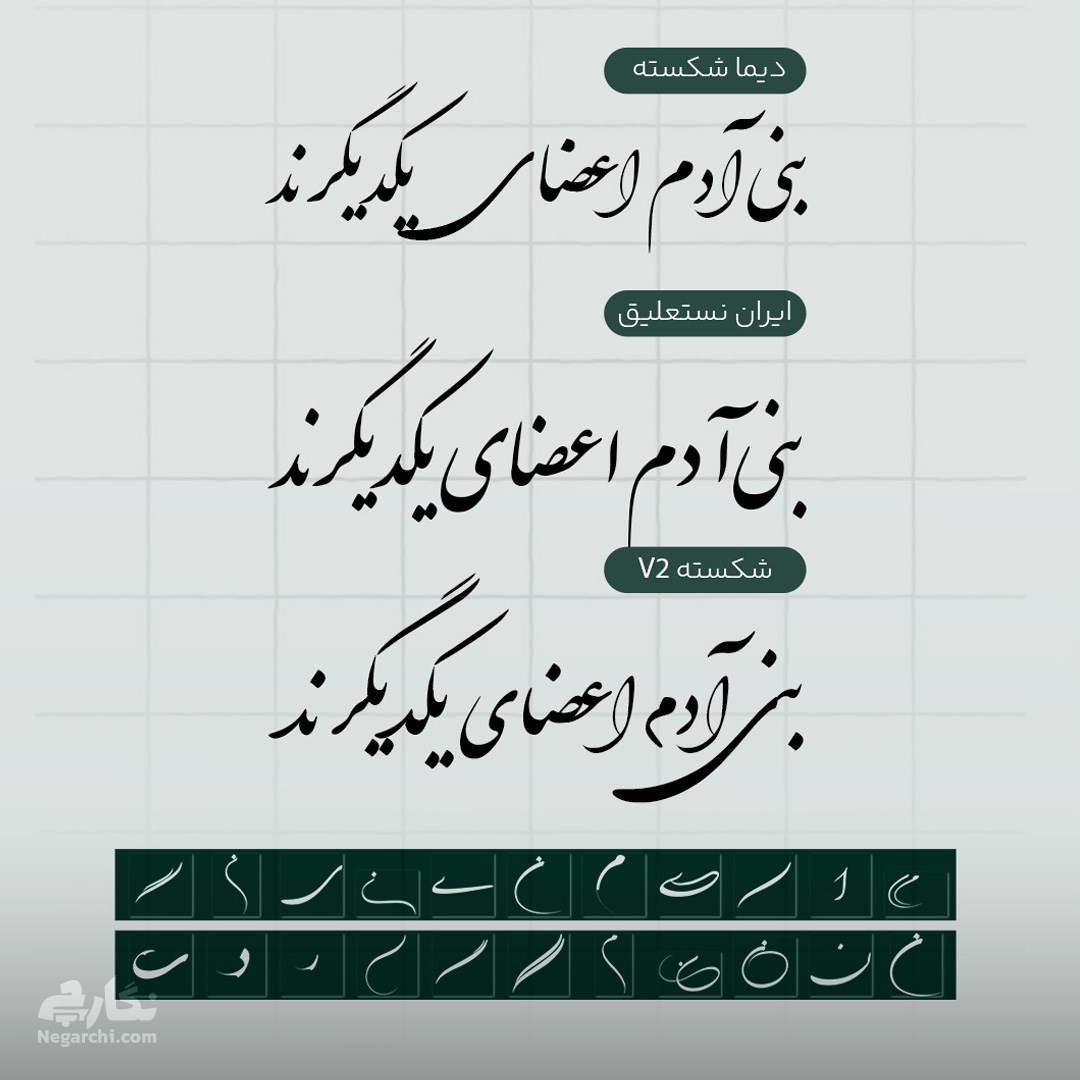
مجموعهای شامل 3 نسخه فونت نستعلیق بههمراه 22 حروف کشیده فارسی نستعلیق با کیفیت بالا. این مجموعه شامل فونتهای دیما شکسته، ایران نستعلیق و نستعلیق شکسته V2 بوده و در فرمتهای TTF و PNG برای استفاده در کامپیوتر و موبایل ارائه شده است.
این مجموعه شامل 3 نسخه فونت نستعلیق به همراه 22 حروف کشیده فارسی نستعلیق است که برای استفاده در طراحیهای تایپوگرافی فارسی و پروژههای هنری آماده شده است. فونتها در فرمت TTF و مجموعه حروف کشیده در فرمت PNG ارائه شدهاند و به راحتی در کامپیوتر و موبایل قابل استفاده هستند.
در این مجموعه سه فونت محبوب و کاربردی یعنی دیما شکسته، ایران نستعلیق و نستعلیق شکسته V2 قرار گرفته است که برای طراحیهای فارسی با سبک سنتی و خوشنویسی بسیار کاربردی هستند.
همچنین 22 حروف کشیده فارسی نستعلیق با کیفیت بالا در این مجموعه قرار دارد که برای افرادی که در زمینه کالیگرافی و طراحی تایپوگرافی فارسی فعالیت میکنند بسیار مناسب است و امکان ایجاد ترکیبهای زیباتر و حرفهایتر در طراحی را فراهم میکند.